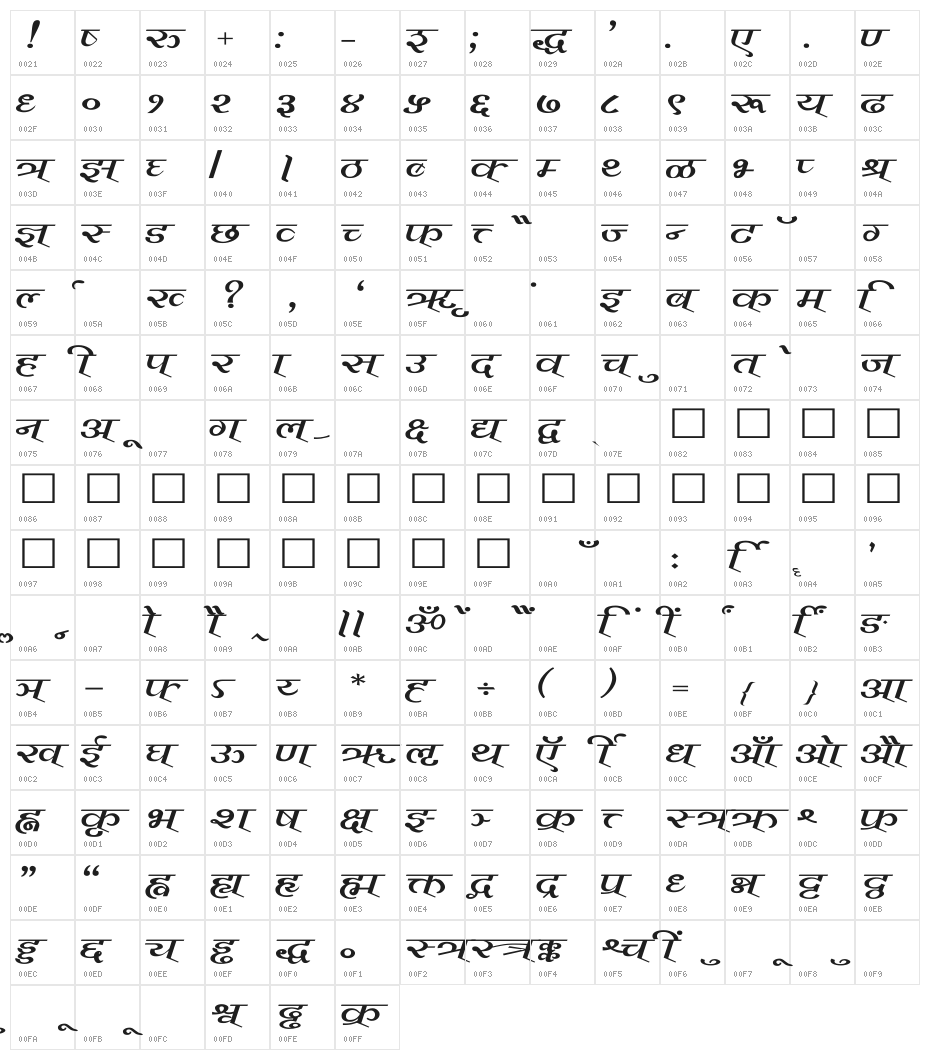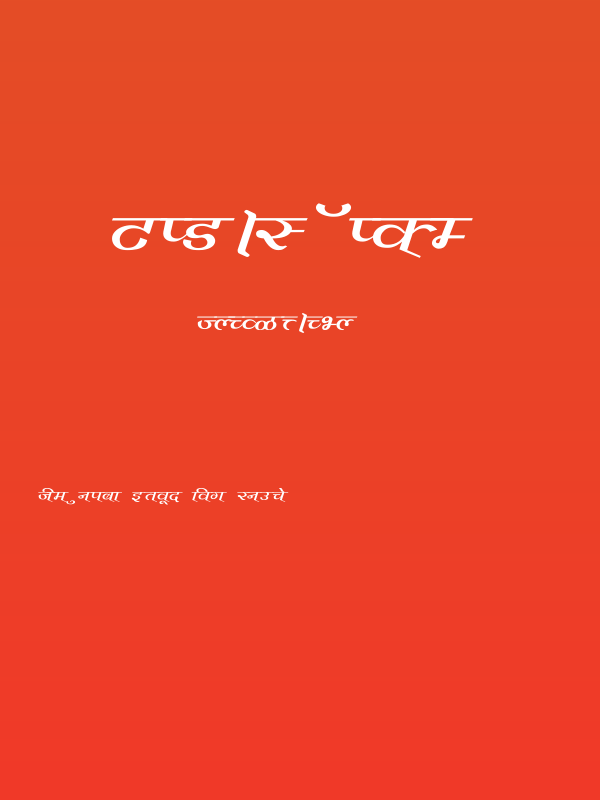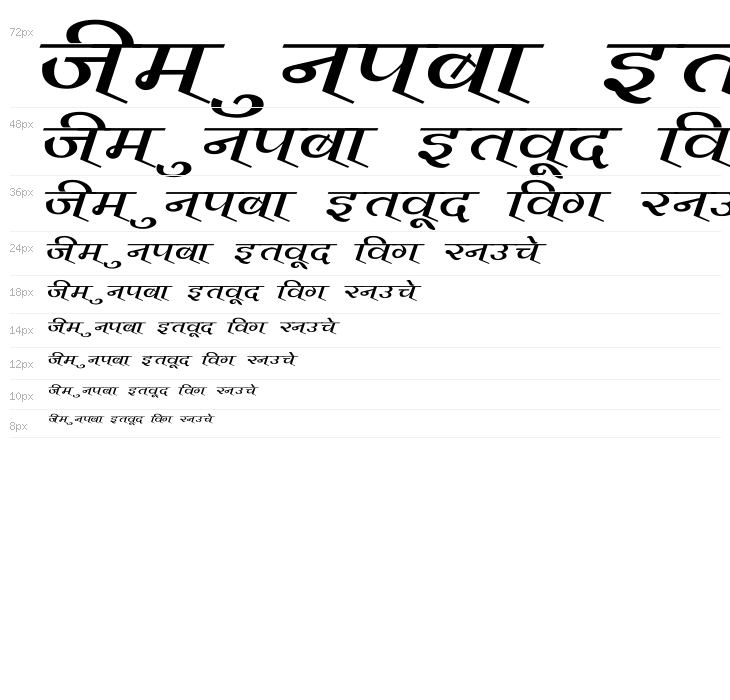
Vimal Wide Font
| Kategorien | Script |
| Gesamtstil | Traditional |
| Anwendungsfall | Headlines, Body text, Cultural projects |
| Vorgeschlagene Projekte | Ideal for cultural publications, educational materials, and artistic projects requiring Devanagari script. |